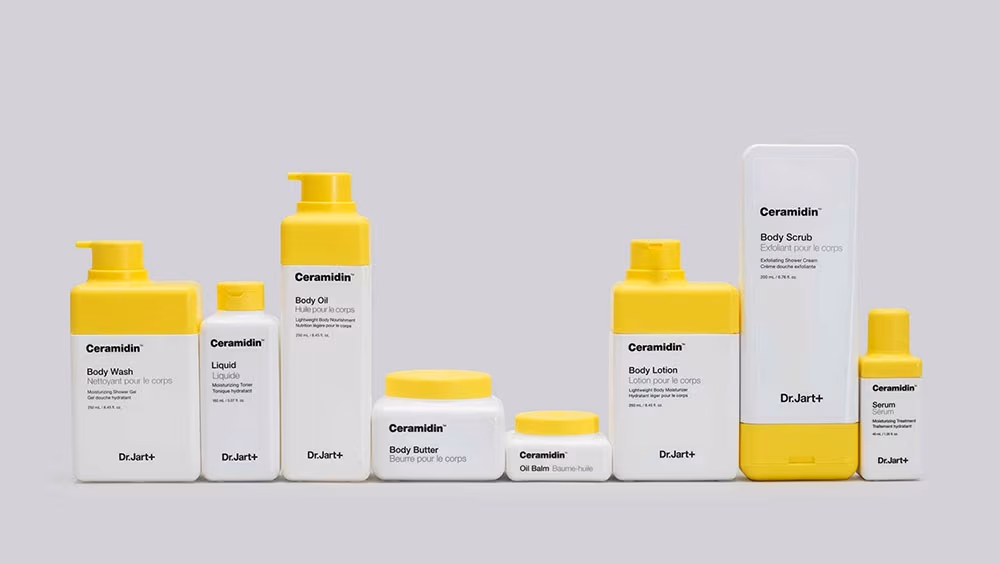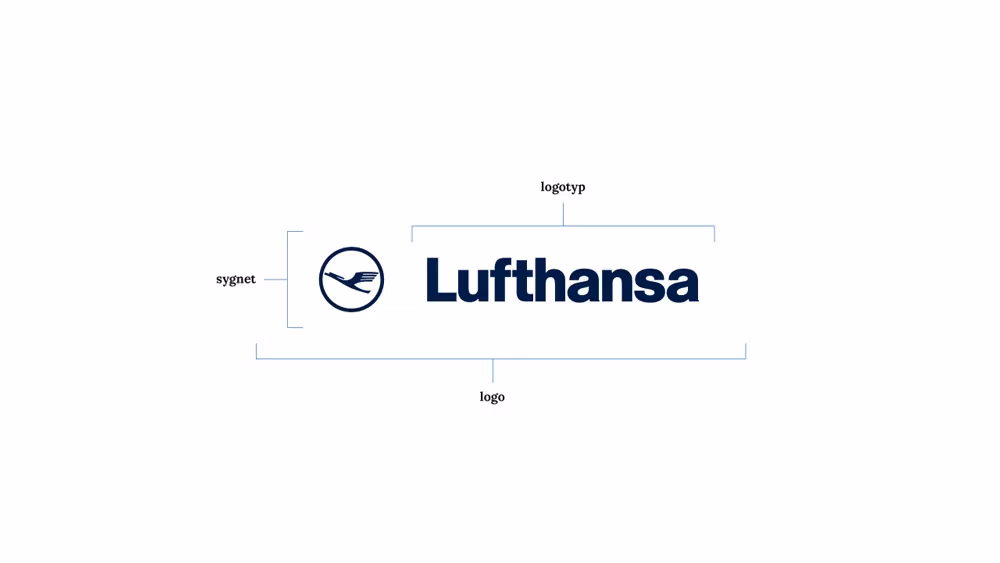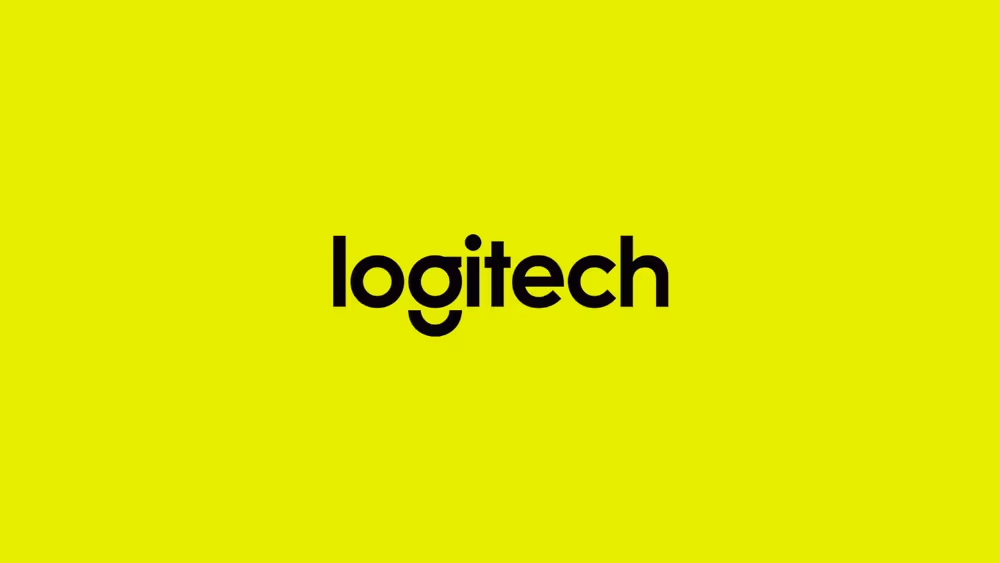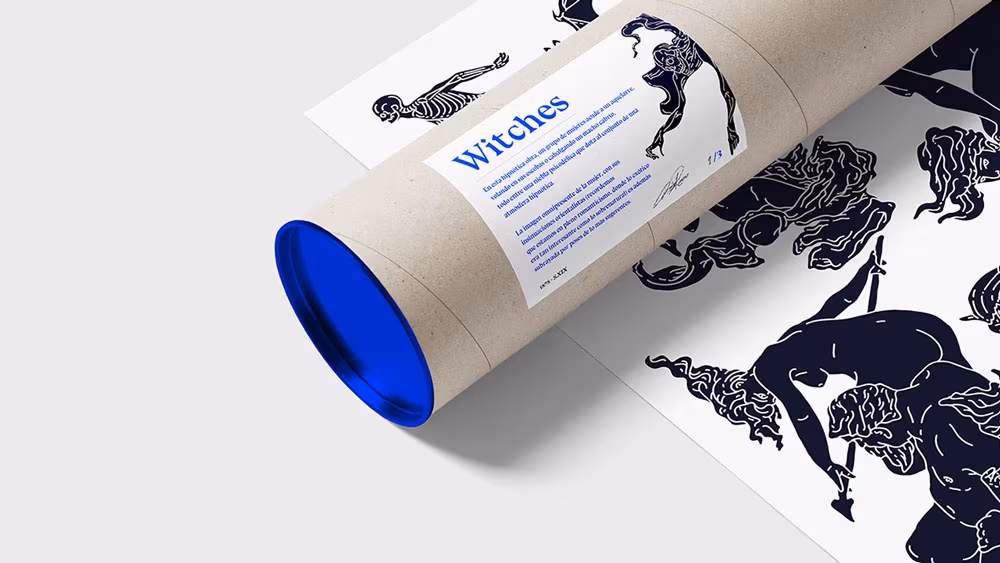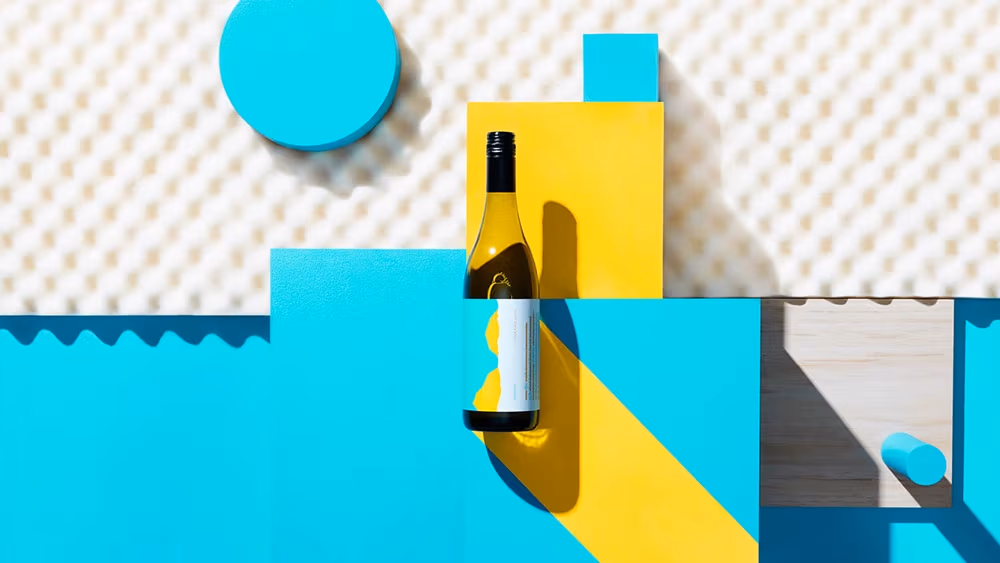
Logo, branding, identyfikacja wizualna — terminy te bardzo często używane są w powszechnej komunikacji. Padają z ust osób niezwiązanych ściśle z projektowaniem – redaktorów, dziennikarzy i zwykłych „Kowalskich” – w wielu przypadkach używane są błędnie.
Definicja kluczowych pojęć
Słowa takie jak „logo” czy „identyfikacja wizualna” są szeroko znane i każdy potrafiłby zdefiniować je na swój sposób, w związku z tym internet zaskakuje mnogością i różnorodnością definicji, które w wielu przypadkach nie są zgodne z prawdą.
Logo czy logotyp, font czy czcionka?
Dr. Jart+, Pentagram
Pojęcia związane z logo bardzo trafnie w swojej książce Symbol opisali Angus Hyland, Steven Bateman, pozwolę sobie więc je przytoczyć:
• Logo – Unikalna i charakterystyczna forma graficzna, stylizowany napis, symbol lub inna forma ekspresji graficznej służąca do identyfikacji marki, firmy bądź organizacji. Umieszcza się je na materiałach drukowanych, reklamach, artykułach piśmienniczych, budynkach i pojazdach.
• Symbol – Abstrakcyjna lub obrazkowa forma przekazu graficznego która reprezentuje istotę tożsamości marki. („Symbol” to kolosalne słowo. Występuje w religii, literaturze i sztuce; to jedna z jego definicji).
• Logotyp – Typograficzna stylizacja nazwy lub słowa, która ma za zadanie identyfikować markę, firmę lub organizację. Wywodzi się z greckiego słowa „logos” – słowo.
• Identyfikacja wizualna – Podstawowe narzędzie służące kreowaniu wizerunki firmy na rynku. Termin ten określa ogół symboli i zachowań stosowanych w firmie w celu uzyskania czytelnej i spójnej identyfikacji rynkowej i wyróżnienia jej spośród konkurencji. Stworzenie spójnego systemu wizualnego jest najważniejszym elementem całościowej identyfikacji.
• Typografia – Sposób graficznego przedstawienia języka za pomocą ruchomych czcionek bądź cyfrowych krojów.
Lufthansa, podział elementów logo
Błędne nazewnictwo – logo czy logotyp?
Podstawowym błędem, spotykanym bardzo często jest mylne traktowanie wyrazu logo i logotyp jako synonimy. Jako poparcie tej tezy mówi się, że wyraz logo to skrót wyrazu logotyp. Nazewnictwo to jest oczywiście błędne – zgodnie z definicjami wyraz logo i logotyp oznaczają dwa odmienne zjawiska, natomiast logotyp może być określony jako logo, zależność ta nie działa w obie strony, zatem wyraz logo jest nadrzędny.
If logo once meant the same as logotype – it no longer does.
— Angus Hyland
Efektem tego błędnego myślenia jest nagminne mylenie składowych logo.
Dlaczego tak ważne jest używanie prawidłowych określeń? Jeśli jesteś początkującym grafikiem to odpowiedź jest bardzo prosta – nie warto już na początku swojej drogi wprowadzać do swojej pracy błędnych nawyków. Dla klientów zrozumienie powyższego diagramu jest również bardzo istotne – ułatwi to komunikację i ścisłe określenie swoich wymagań, potrzeb w rozmowie na temat projektu.
Znaczenie typografii
Typografia – jeden z podstawowych elementów identyfikacji wizualnej – bardzo często nie jest traktowany z należytą mu uwagą. Należy tutaj zaznaczyć, że jest to kluczowa część, bowiem litery to swego rodzaju pomost pomiędzy częścią wizualną projektu, a przekazywanym komunikatem słownym. To właśnie poprzez wybór odpowiedniego kroju pisma nadajemy naszym słowom odpowiedni kontekst, a oprócz wiadomości, przekazujemy również emocje.
Logitech logo, DesignStudio
• Typografia – Sposób graficznego przedstawiania języka za pomocą ruchomych czcionek bądź cyfrowych krojów.
• Minuskuła – (małe litery; ang lowercase). W typografii: zestaw małych liter alfabetu.
• Majuskuła – (wielkie liter, wersalki, ang. uppercase). W typografii: zestaw wielkich liter alfabetu.
• Rodzina pisma – Zbiór wszystkich kształtów i znaków pisma w różnych odmianach, zaprojektowanych według wspólnego kryterium, ujętych pod tą samą nazwą.
• Czcionka – W drukarstwie tradycyjnym każdy z metalowych słupków, na których znajduje się odlany znak pisma.
• Font – Termin określający plik cyfrowy, który zawiera dane dotyczące jednej odmiany rodziny pisma, zakodowany w określony sposób (OpenType, PostScript, TrueType itp.).
• Interlinia – Przestrzeń pomiędzy dwoma wierszami złożonego tekstu. W składzie ręcznym była to przestrzeń pomiędzy dwoma rzędami czcionek ustalana za pomocą metalowej sztabki. W składzie cyfrowym jest to odległość mierzona pomiędzy bazowymi liniami pisma dwóch kolejnych wersów tekstu.
• Glif – (ang. glyph). Graficzne przedstawienie znaku pisma, w odróżnieniu od samego znaku, który jest pojęciem abstrakcyjnym. Na przykład glif przedstawiający znak wielkiej litery A alfabetu łacińskiego może także przedstawiać znak wielkiej litery alfa z alfabetu greckiego.
• Grubość (ciężar; ang. weight). Cecha różnych odmian jednej rodziny pisma uzależniona od modyfikacji grubości kresek.
• Światło – niezadrukowana przestrzeń.
• Kerning – Ustalenie właściwego światła między parą znaków. Szereg korekt, wynikających z faktu, że światła naturalne nie wystarczają, by osiągnąć optymalne ustawienie znaku.
Definicję pochodzą ze słowniczka pojęć, który możecie odnaleźć w publikacji Jak projektować kroje pisma. Od szkicu do ekranu autorstwa Cristóbala Henestrosa, Laury Meseguer, Joséa Scaglione.
„Font, nie czcionka!”
Wyraz font to często używany anglicyzm, określający cyfrową formę kroju pisma. Określenie to jest fachowe, ściśle wskazujące na rodzaj dystrybucji, jest to zatem dokładniejsze wyrażenie językowe od pojęcia krój pisma – które może oznaczać zarówno font jak i czcionkę.
Niestety, w języku polskim próżno szukać równie wygodnego w użytkowaniu odpowiednika fontu – po polsku precyzyjnie możemy zastąpić go jedynie wyrażeniem cyfrowy krój pisma – co jest bardzo problematyczne i niewygodne.
Należy jednak zaznaczyć, że oba określenia – font i czcionka – są poprawne językowo, w gruncie rzeczy nazywają to samo zjawisko. Jednakże, wyraz font jako określenie cyfrowej formy czcionki, przyjął się już w języku polskim na tyle, że zalecam stosowanie obu tych form na określanie dwóch innych rodzajów dystrybucji krojów pisma.
Istota logo w budowaniu świadomości marki
Bez wątpienia należy uznać logo za podstawowy budulec identyfikacji wizualnej, jest to filar od którego należy zacząć, to właśnie w procesie projektowania logo kreujemy bazowe elementy wizualnej tożsamości marki.
Identyfikacja wizualna jest jednak pojęciem bardziej skomplikowanym, złożonym z wielu elementów. Logo jest najważniejsze i często widoczne na pierwszy rzut oka. Jednak idąc za definicją – jest to szereg symboli, zachowań i form używanych w jednym, ściśle zdefiniowanym kontekście.
Oczywistymi elementami identyfikacji jest logo, określona kolorystyka, spójny język projektowania – ale także — scenariusz zachowań wobec klienta, sposób komunikacji z ogółem rynku czy chociażby ściśle ustalony układ sklepów.
Przykładowe, najpowszechniejsze składowe:
• Key visual – Język wizualnej komunikacji marki. Określa podstawowe zasady projektowania materiałów związanych z podmiotem. W przypadku globalnych firm jest bardzo rozbudowany i dokładnie opisany; jest podstawą i gwarantem utrzymywania spójności identyfikacji wizualnej.
• Materiały drukowane – Wizytówki, etykiety, faktury, papier firmowy, teczki reklamowe, ulotki, artykuły piśmiennicze. To wszędzie tutaj aplikujemy wcześniej wymieniony key visual nie zapominając o dobrodziejstwach uszlachetniania druku i ich ogromnym wpływie na końcowy efekt – komunikat niewerbalny wysłany do potencjalnego klienta.
• Typografia – Opisane zasady stosowania krojów w obrębie identyfikacji wizualnej. To tutaj określa się konkretne kroje, grubości a także tworzy się wstępne zarysy później aplikowanych stylów akapitowych. Odpowiednio dobrana typografia wzbudza wybrane emocje i przekazuje idee.
• Oznaczenie pojazdów – Bardzo ważny element w przypadków marek zajmujących się ściśle transportem, komunikacją. To właśnie poprzez oznaczenia pojazdów klient spotyka się najczęściej z identyfikacją swojego przewoźnika. Wyszczególniane są tutaj wszelkie oznaczenia zewnętrzne pojazdów, umiejscowienie logo, dodatkowej typografii a także wymaganych dodatkowych elementów (na przykład dopuszczalnej ładowności wagonów). Poprawnie zaprojektowana szata graficzna pozostaje w pełni spójna z tożsamością wizualną jednostki.
• Dodatkowe elementy – Tak jak wspomniałem wcześniej, każdy podmiot cechuje się indywidualnymi zmiennymi, każda marka zakłada unikalny plan rozwoju, więc elementy na które kładzie się największy nacisk będą inne. W tym artykule chciałem opisać te, które pojawiają się najczęściej.
Identyfikacja Witches
Witches
Jak skutecznie panować nad przestrzeganiem zasad identyfikacji?
Pierwszym krokiem jest stworzenie księgi znaku, zawierającej wszelkie zasady stosowania logo. Można w tym wypadku uciec się do zaprojektowania rozszerzonej księgi znaku, zawierającej ścisłe i szczegółowe zasady projektowania i rozwijania wszystkich elementów które w jakikolwiek sposób łączą się z marką.
Rozwiązania takie są skuteczne w przypadku większych podmiotów, których identyfikacja musi być wdrażana przez wiele pomniejszych siedzib, jednostek. W przypadku mniejszych firm zalecam oddanie się pod opiekę graficzną do jednej agencji lub freelancera, który skutecznie zadba o nasz wizerunek.
Więcej szczegółowych informacji na temat księgi znaku znajdziecie w tym artykule.
Identyfikacja Versions
Versions
Podsumowując…
• Logo to nie logotyp;
• Logo jest jedynie filarem, szczytem góry lodowej, identyfikacji wizualnej. Jest jej podstawą, ale samoistnie nie tworzy całego wyrazu tożsamości wizualnej;
• Język wizualny identyfikacji wizualnej key visual nakreśla ogólny charakter projektów w obrębie identyfikacji;
• Zachowanie jednorodności zapewnia szczegółowa księga znaku;
• Skuteczne budowanie spójnej marki jest kluczowe;